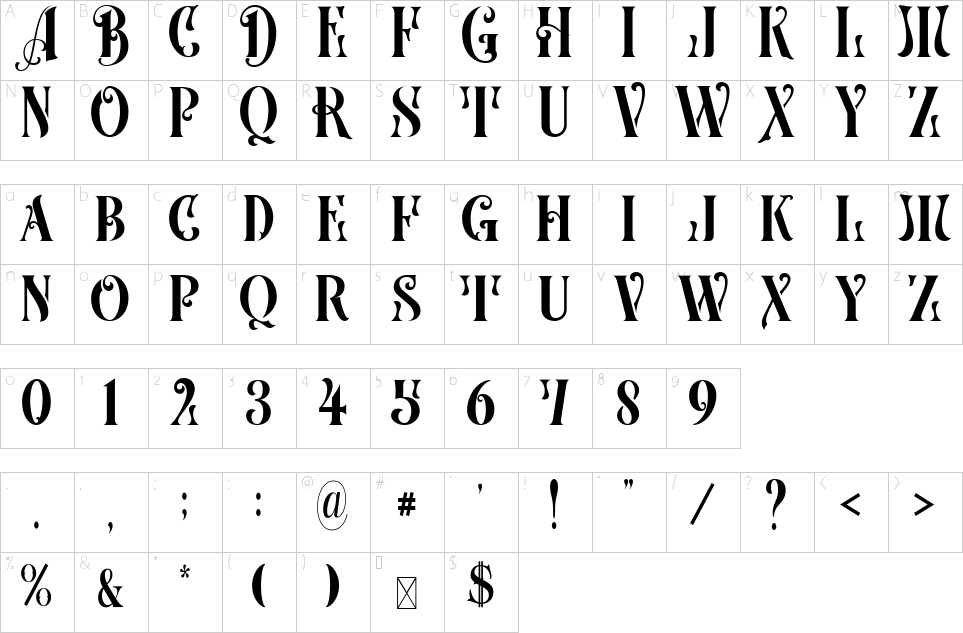
Descubra Albrega Changes, uma fonte gratuita que adere à elegância moderna e sofisticada. Embora não possamos fornecer detalhes específicos sobre o design, sabemos que Albrega Changes foi criada pela 177Studio.com. Este projeto oferece uma fonte de alta qualidade para usuários Windows e Mac, que está disponível gratuitamente para uso. Desde sua disponibilização, a fonte Albrega Changes já foi baixada mais de 2.255 vezes. Se você está procurando por uma fonte que não comprometa seu orçamento e valoriza sua criatividade, Albrega Changes pode ser a escolha perfeita para você.